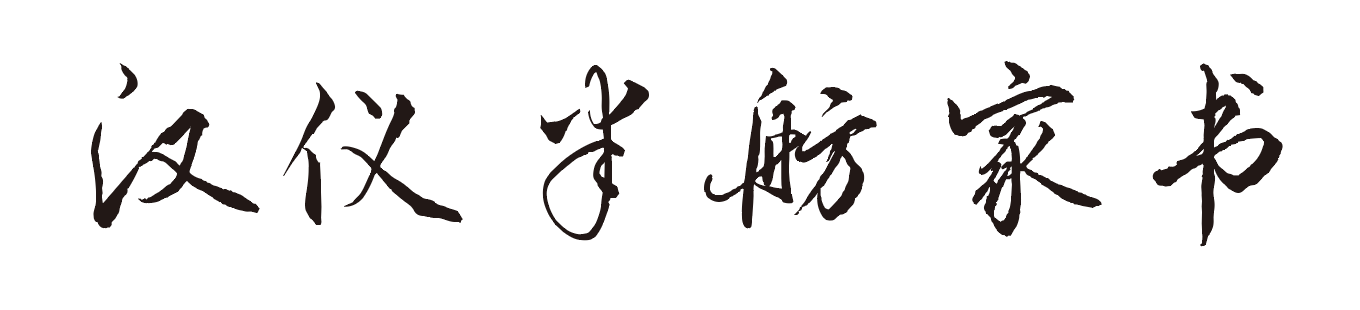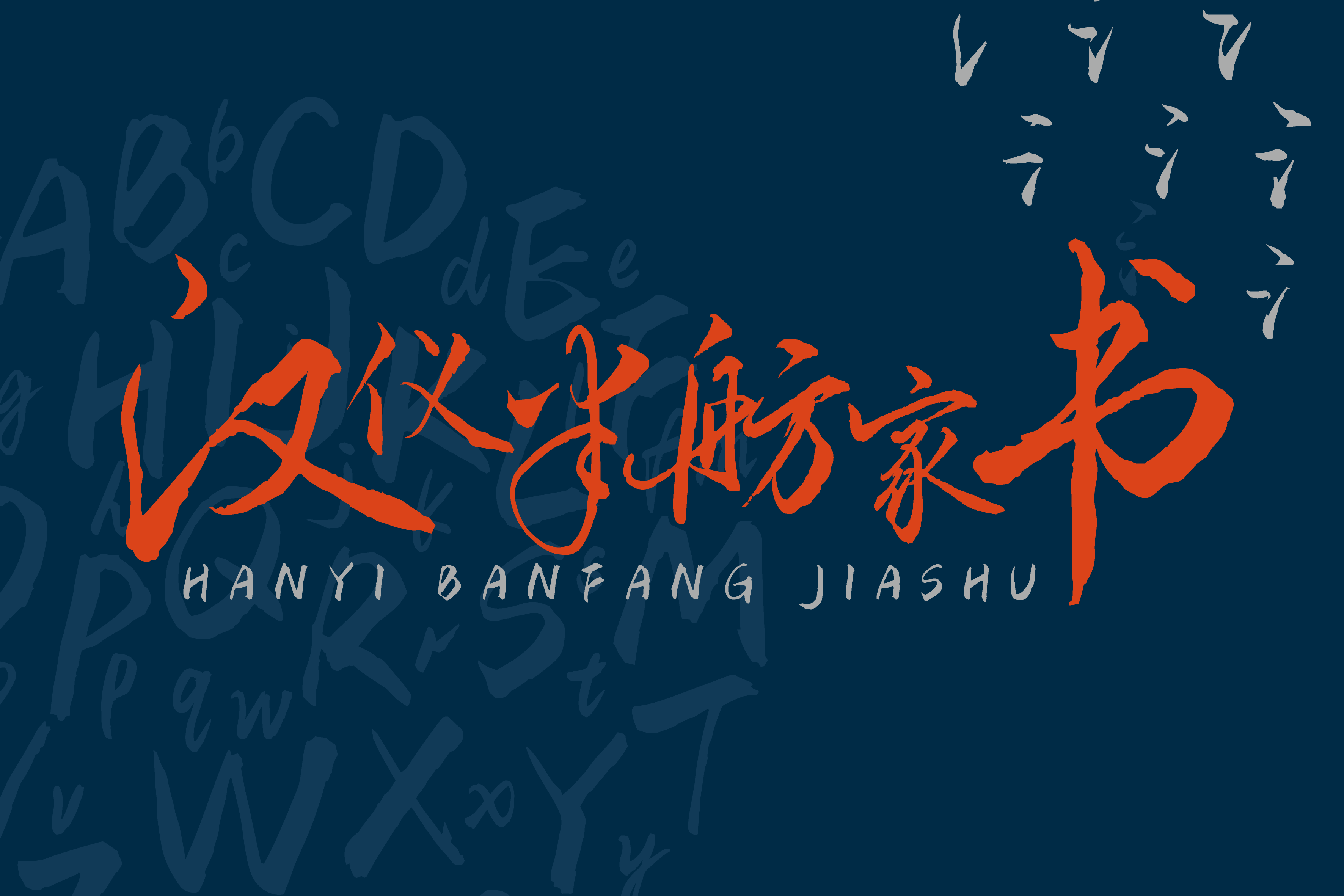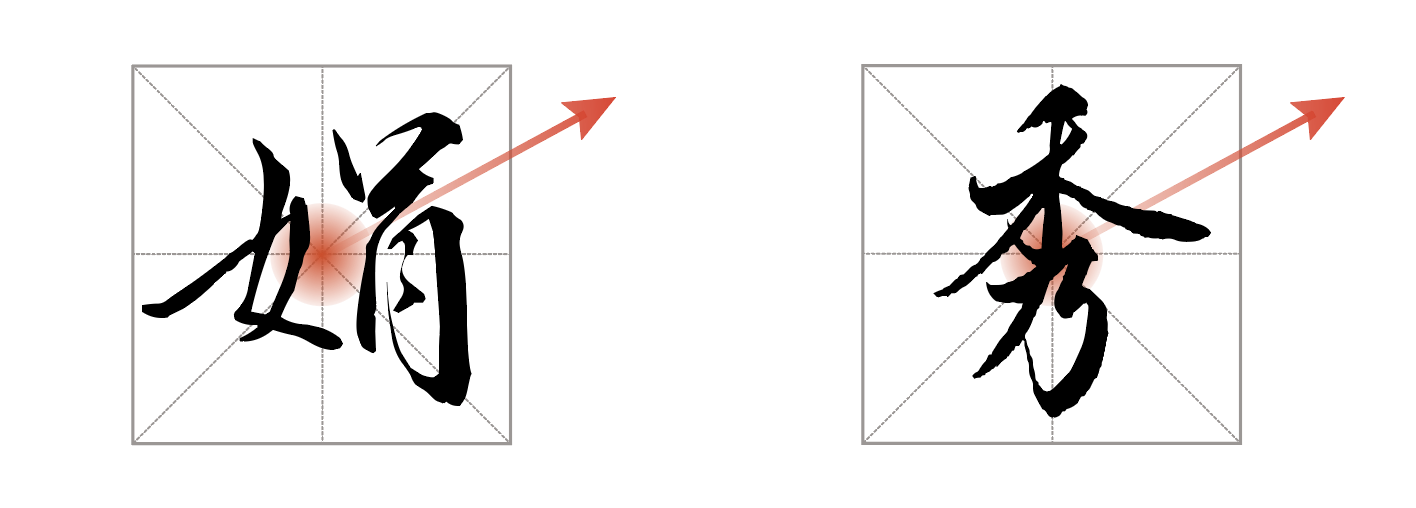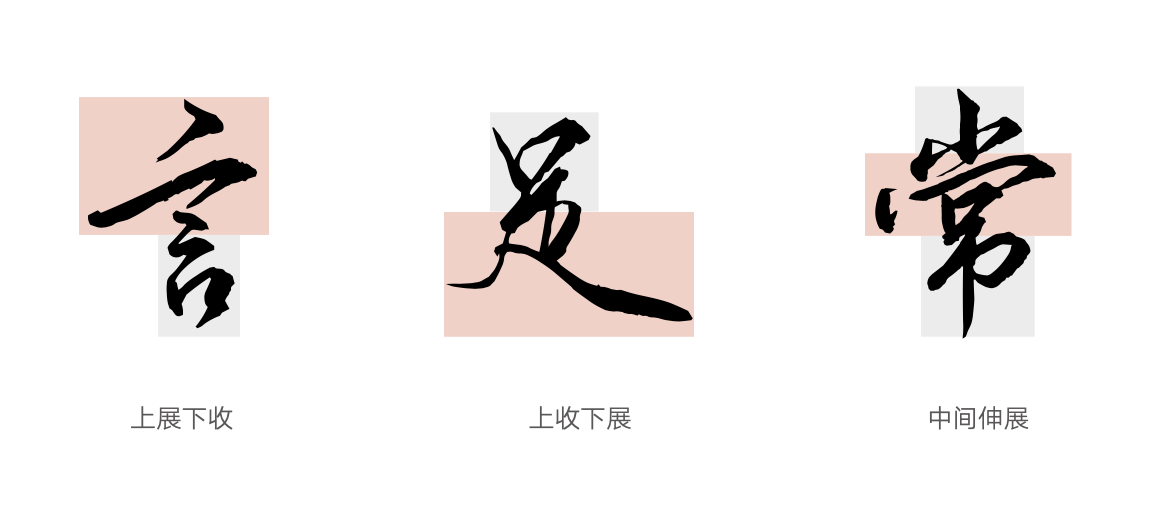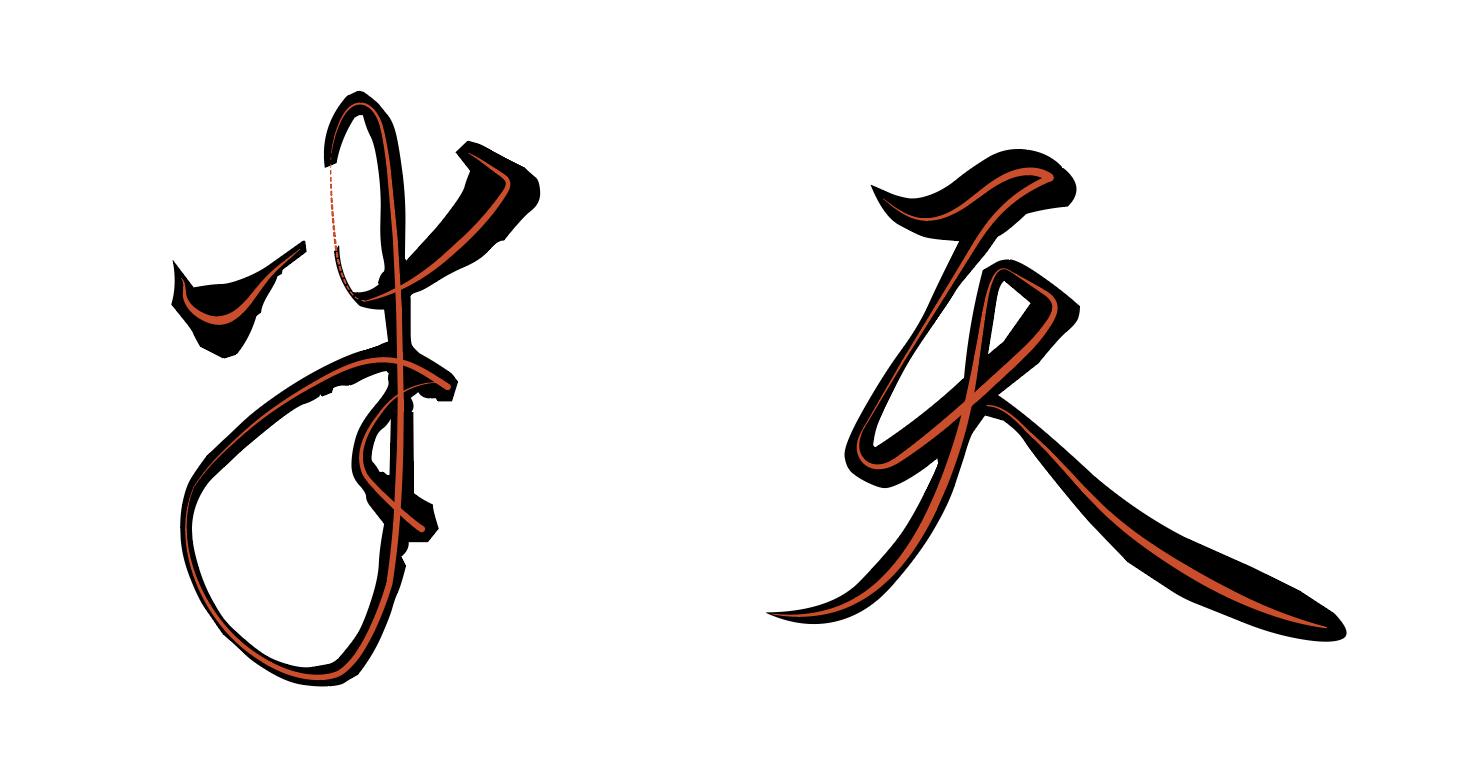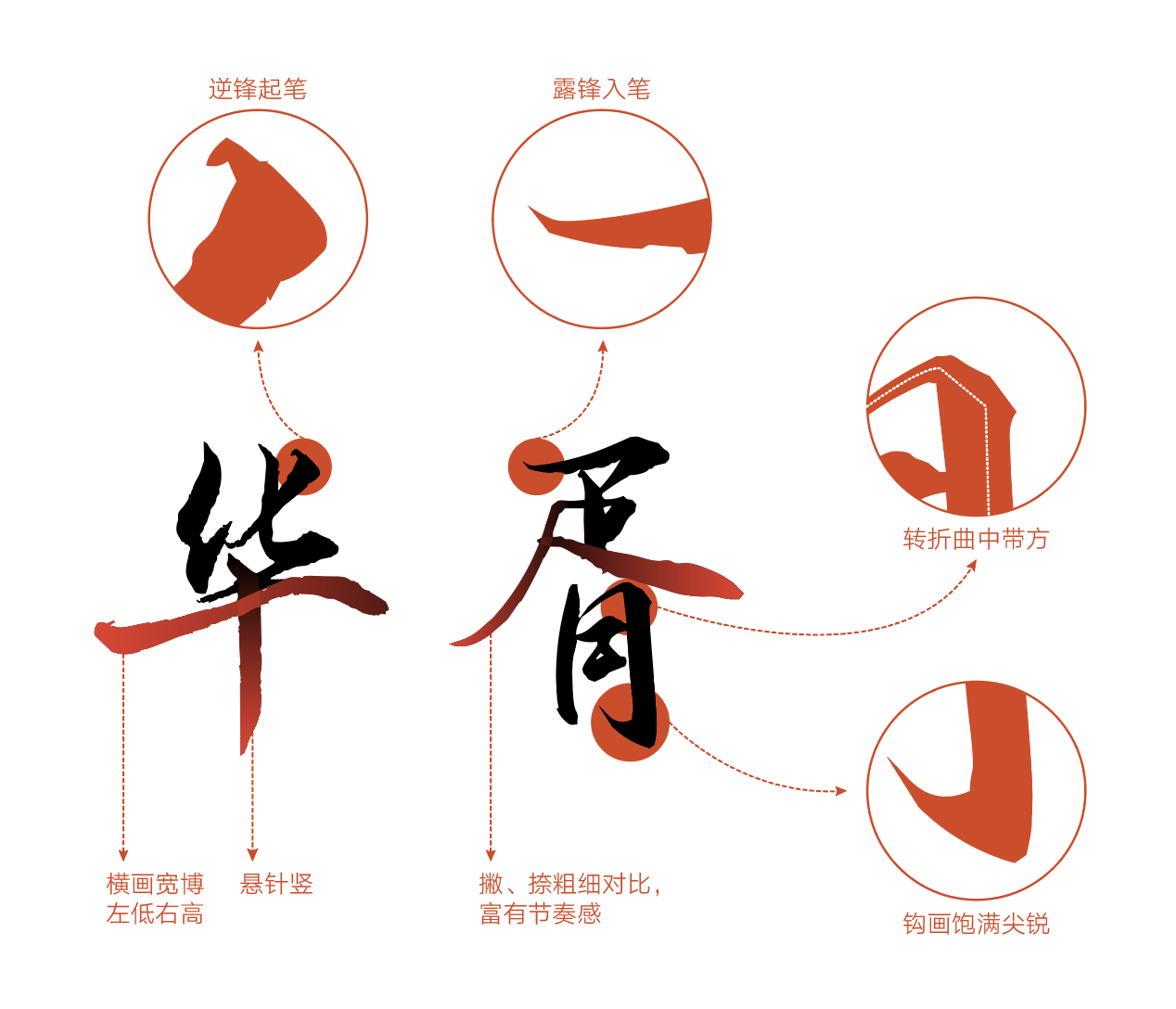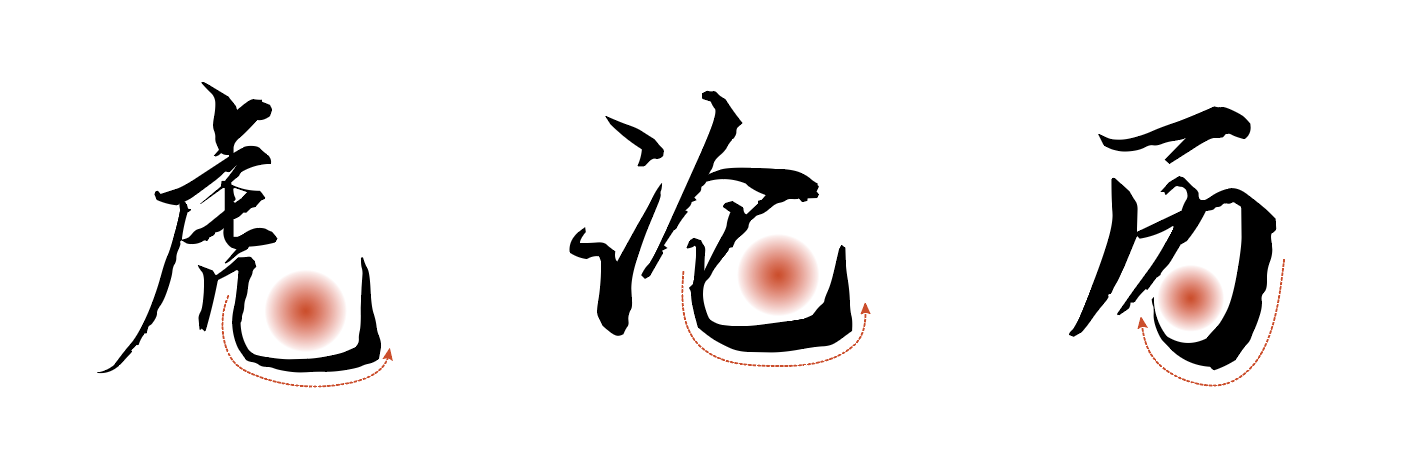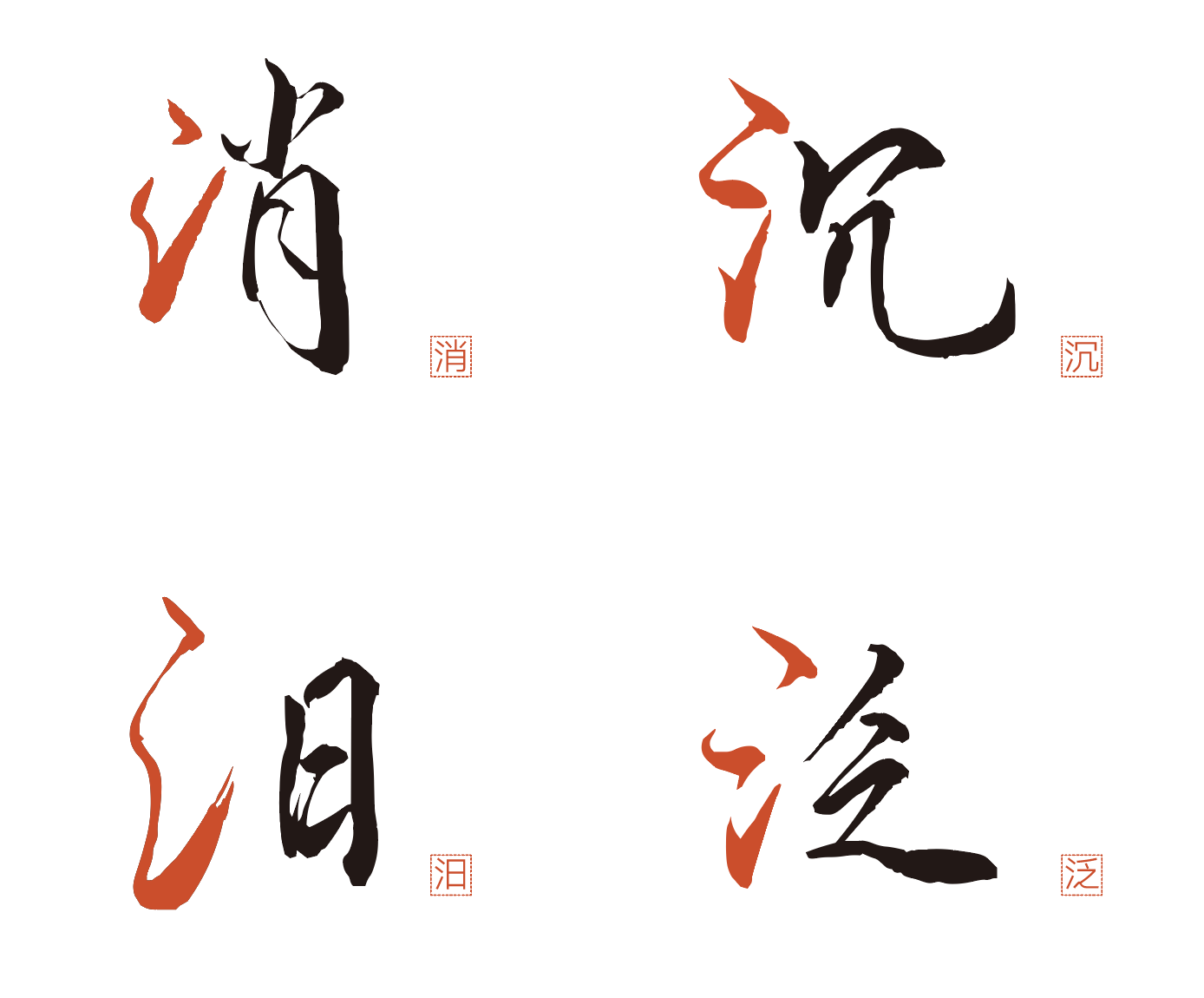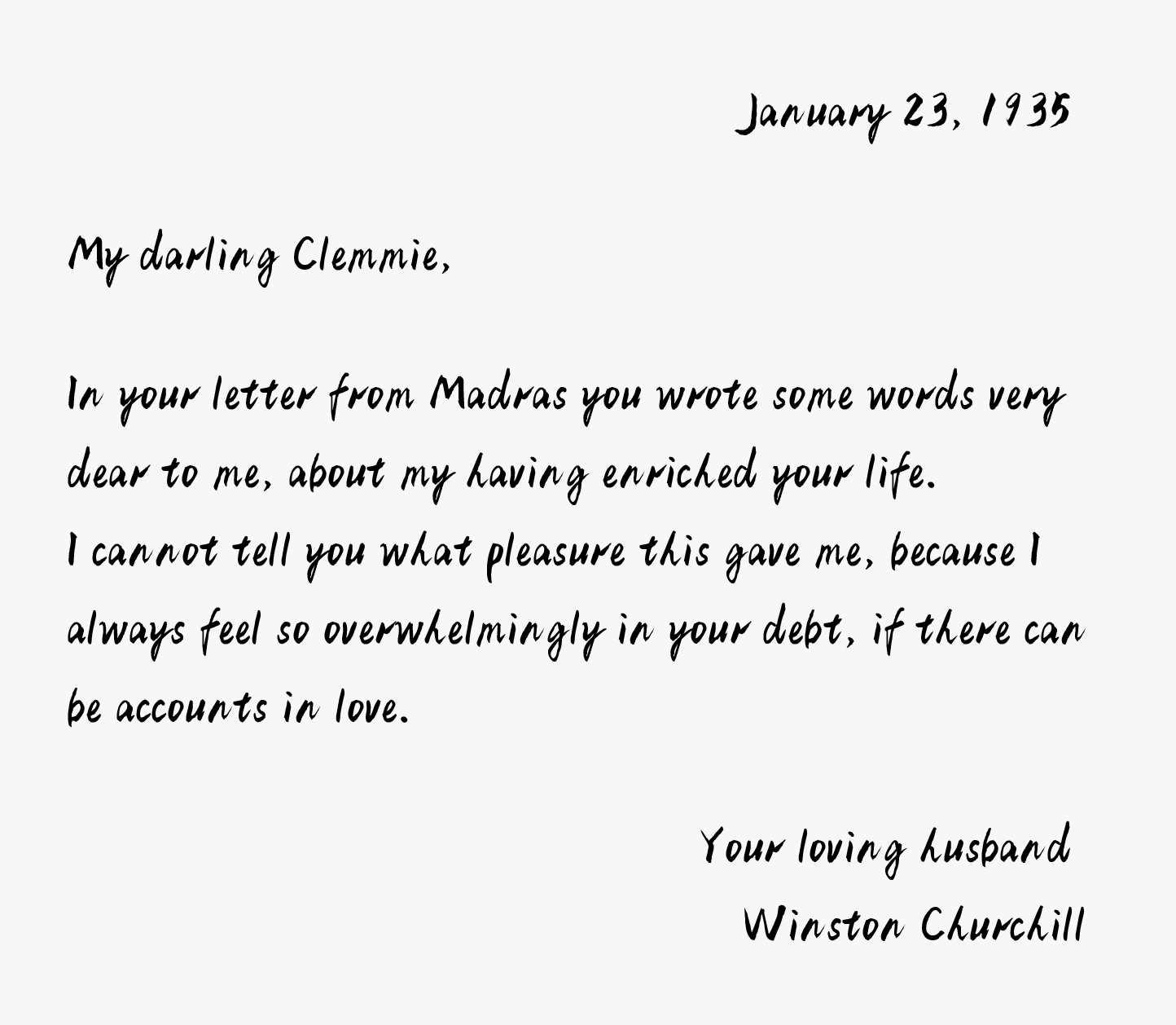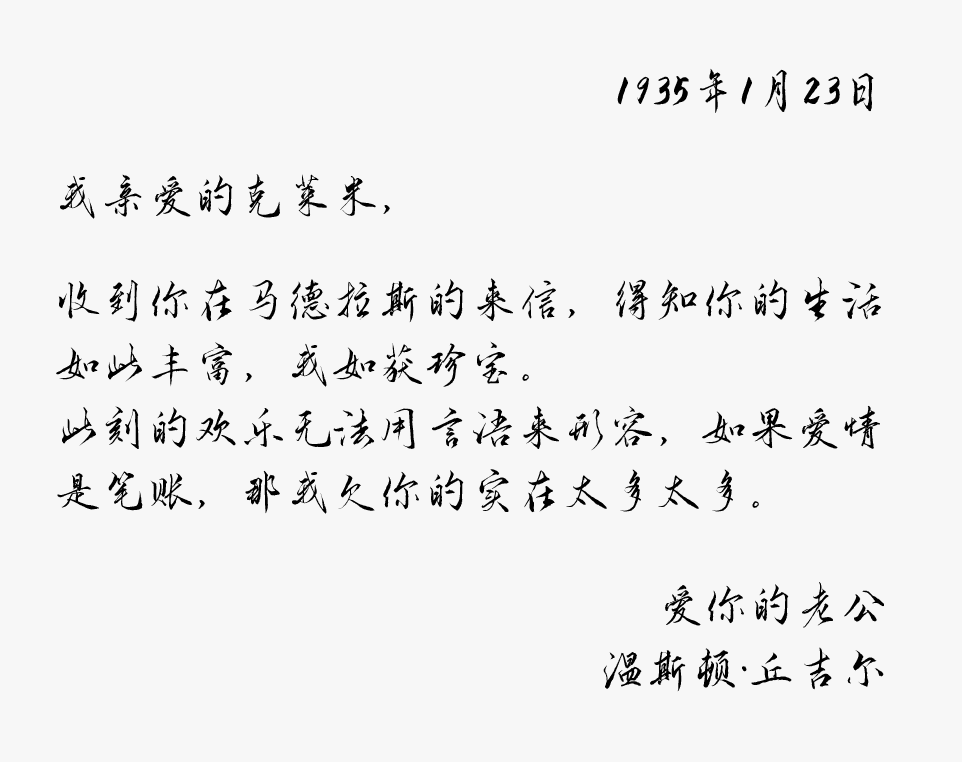
汉仪半舫家书字体介绍,一款软笔书写字体
软笔书写
中国风 / 古典 / 秀丽 / 飘逸
标志LOGO / 品牌广告 / 电影海报 / 书籍封面 / 书信诗歌 / 产品包装 / 影视字幕
背景介绍
汉仪半舫家书是由知名写字博主、汉仪签约字体设计师桥半舫书写创作的一款软笔书写字体。字体充分还原了书写手稿的字形特点,细节表现十分完整。可广泛用于海报、书籍、诗歌排版、影视字幕及产品包装等领域。
字体灵秀飞动
汉仪半舫家书是一款古味淡雅、俊逸灵秀的字体。字体的整体态势均向右上方倾斜,字形飘逸,气势流畅。
结构劲健洒脱
汉仪半舫家书的用笔清爽,字迹连绵潇洒,不同汉字结构的字面差异较大, 富有韵律美。
笔画轻盈洒脱
作者用笔轻松若不经意,有种行云流水般的美感。笔画线条细长、婉转、流畅,极具视觉享受。
汉仪半舫家书的字形飘逸而富有浪漫气息。作者用笔中锋为主,书写牵丝轻盈,强烈的个人风格,贯穿了字体的笔画转折间。
汉仪半舫家书的线条流畅有弹性,笔画遒劲有张力,字体空间浑圆饱满,展现出了一种英气和秀气。
汉仪半舫家书保留了手写的多样性,偏旁部首姿态各异,表现力丰富。
中西文匹配
汉仪半舫家书的西文同样用秀丽笔书写,融入了中文书法的手写方式。笔触丰富,运笔流畅,手写感强,中西文的搭配和谐统一。